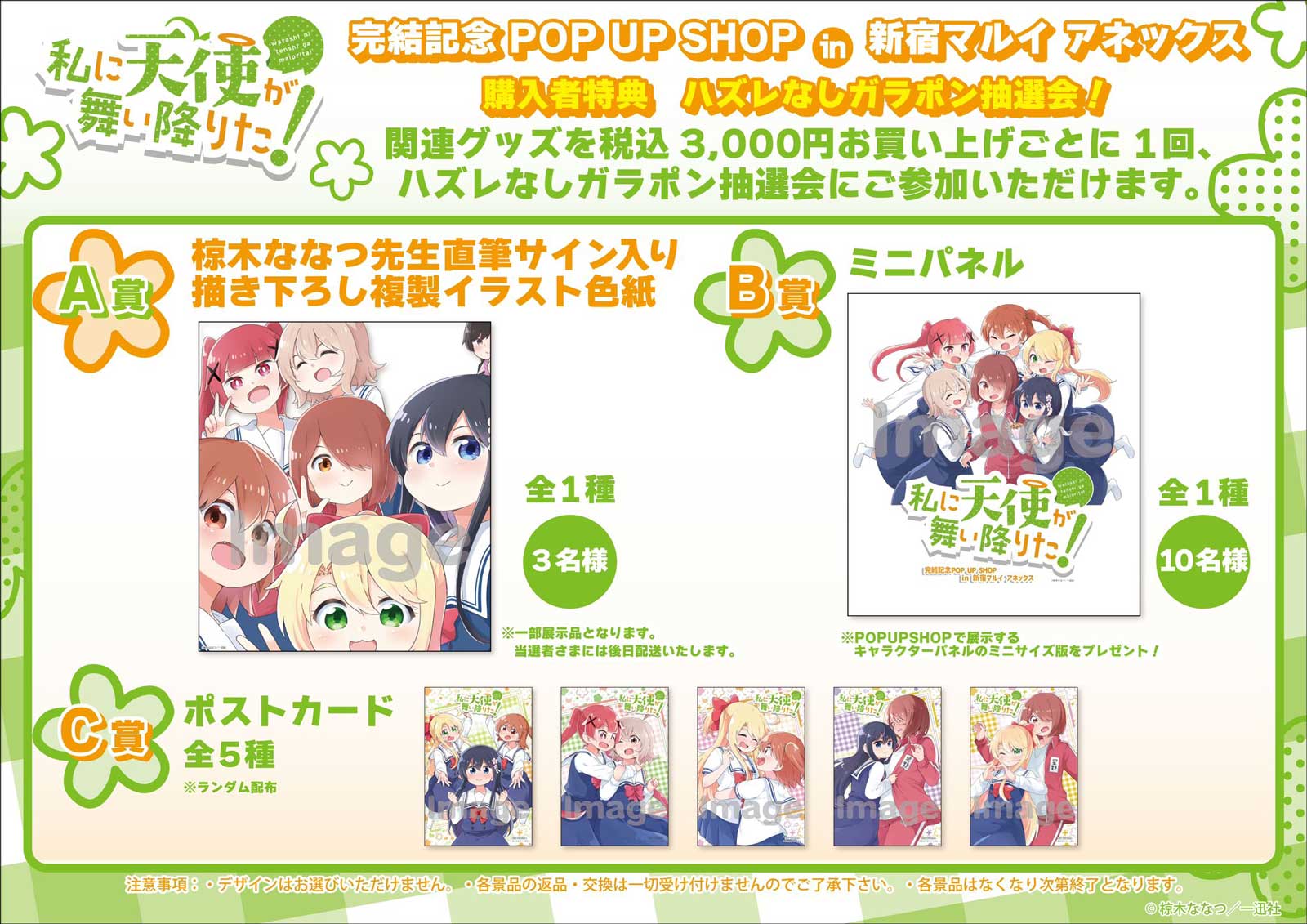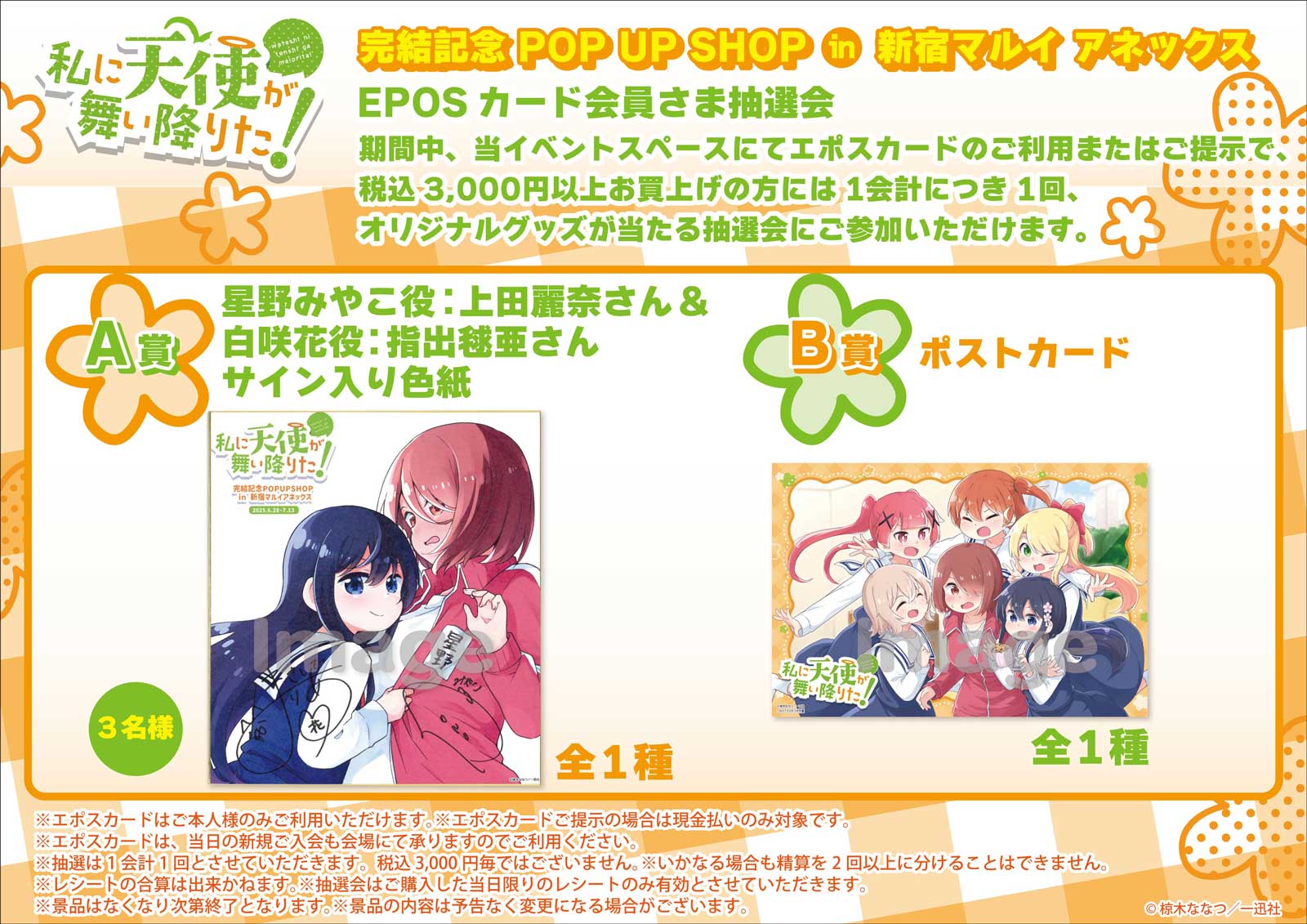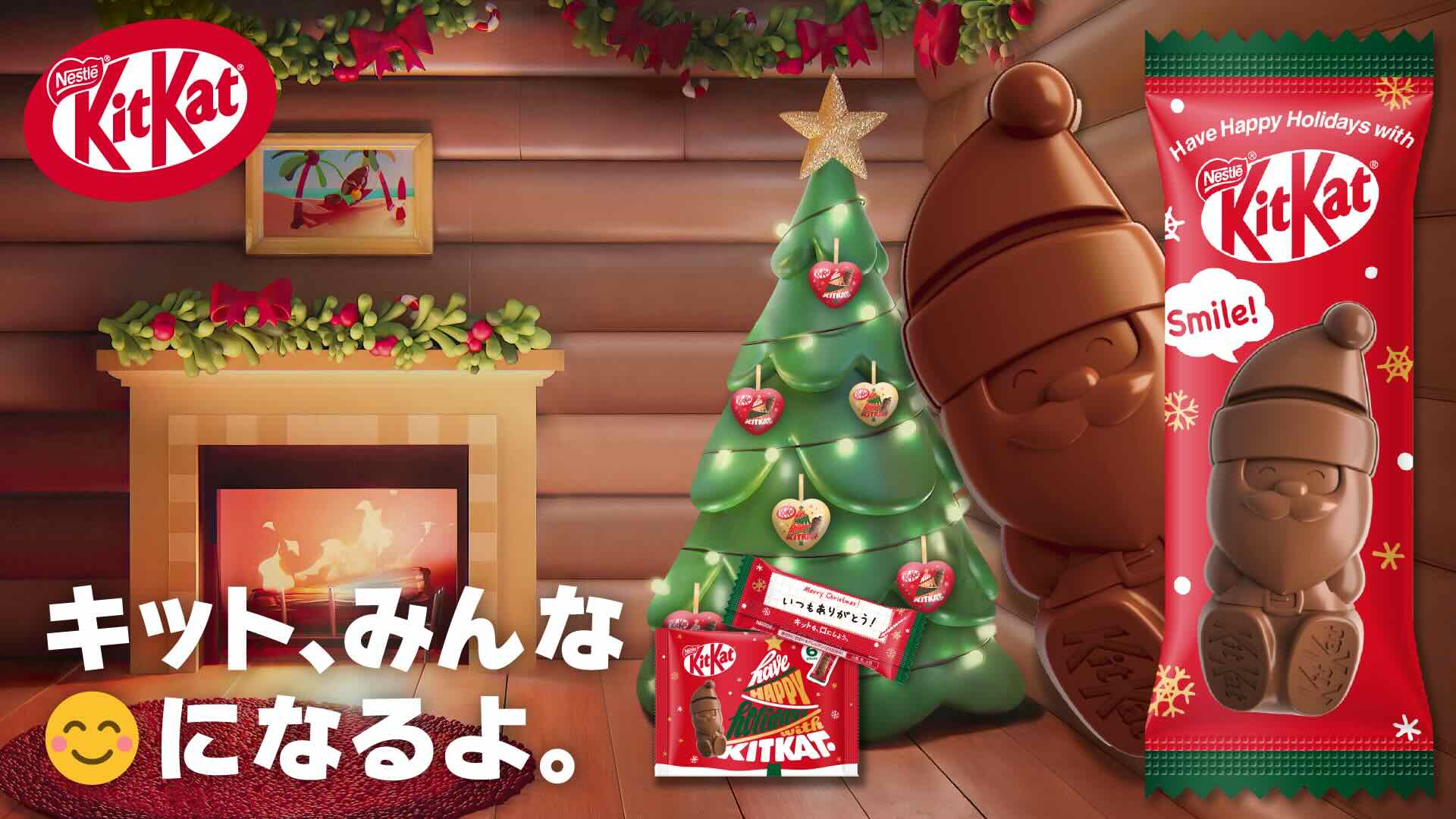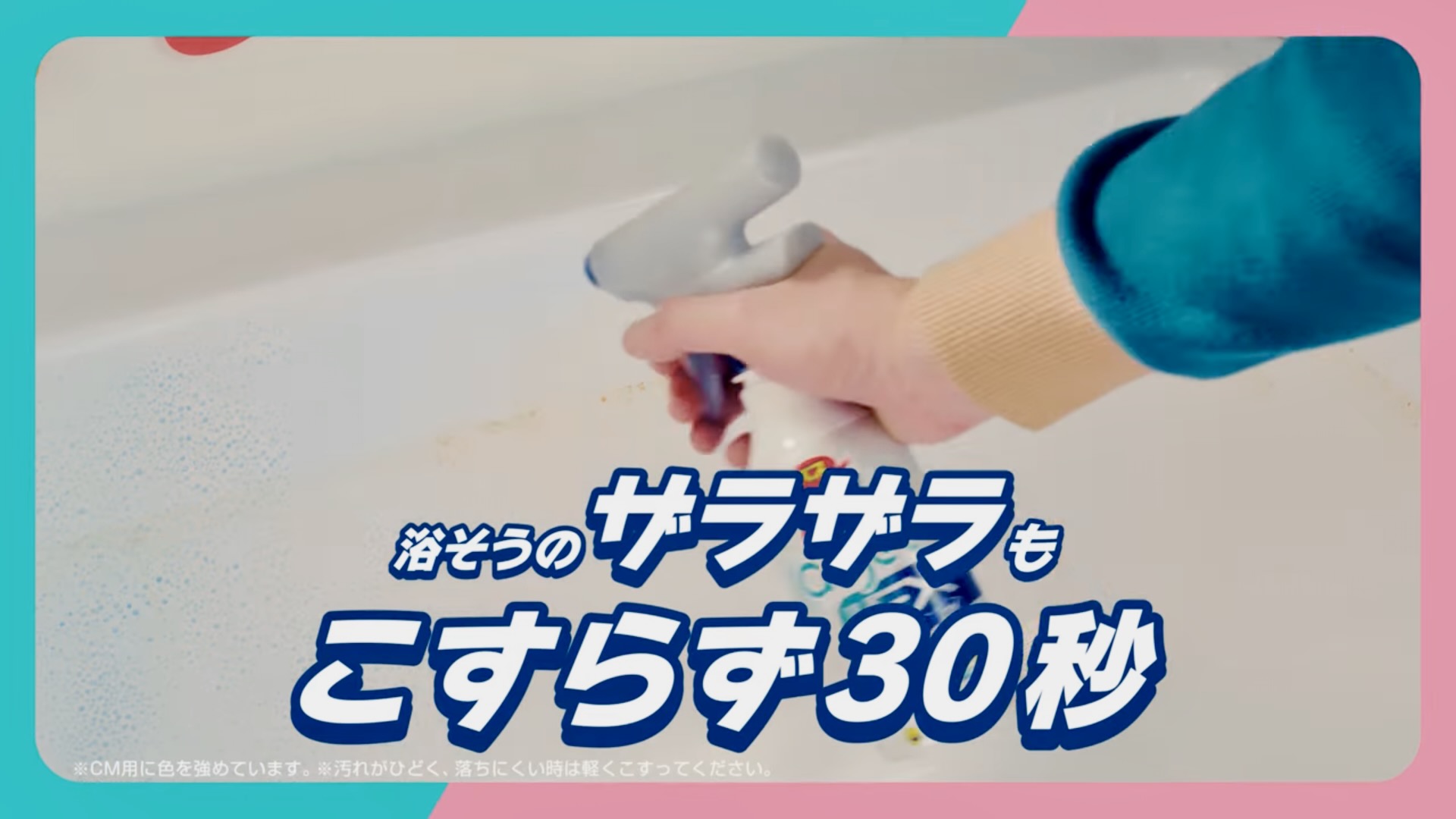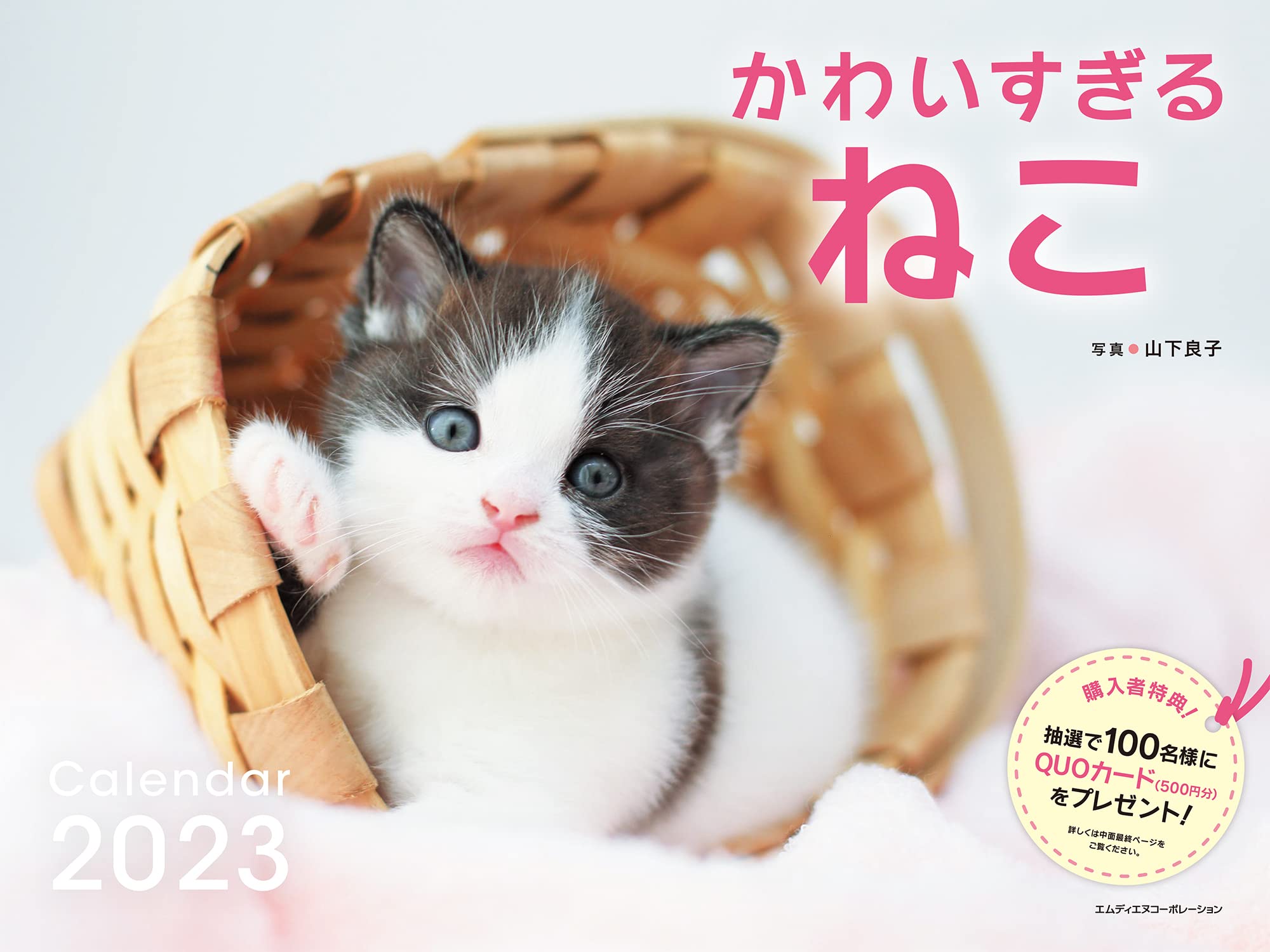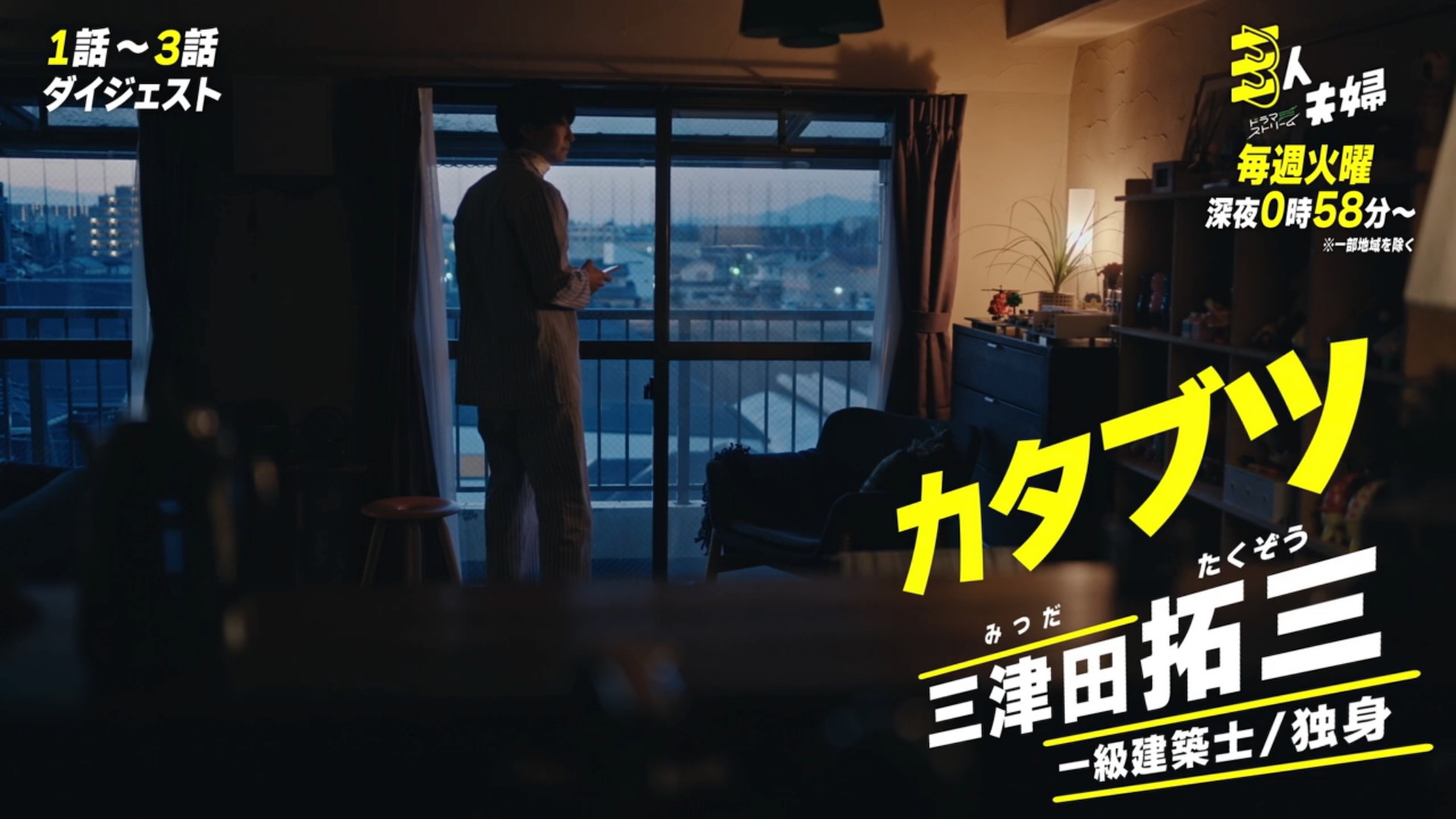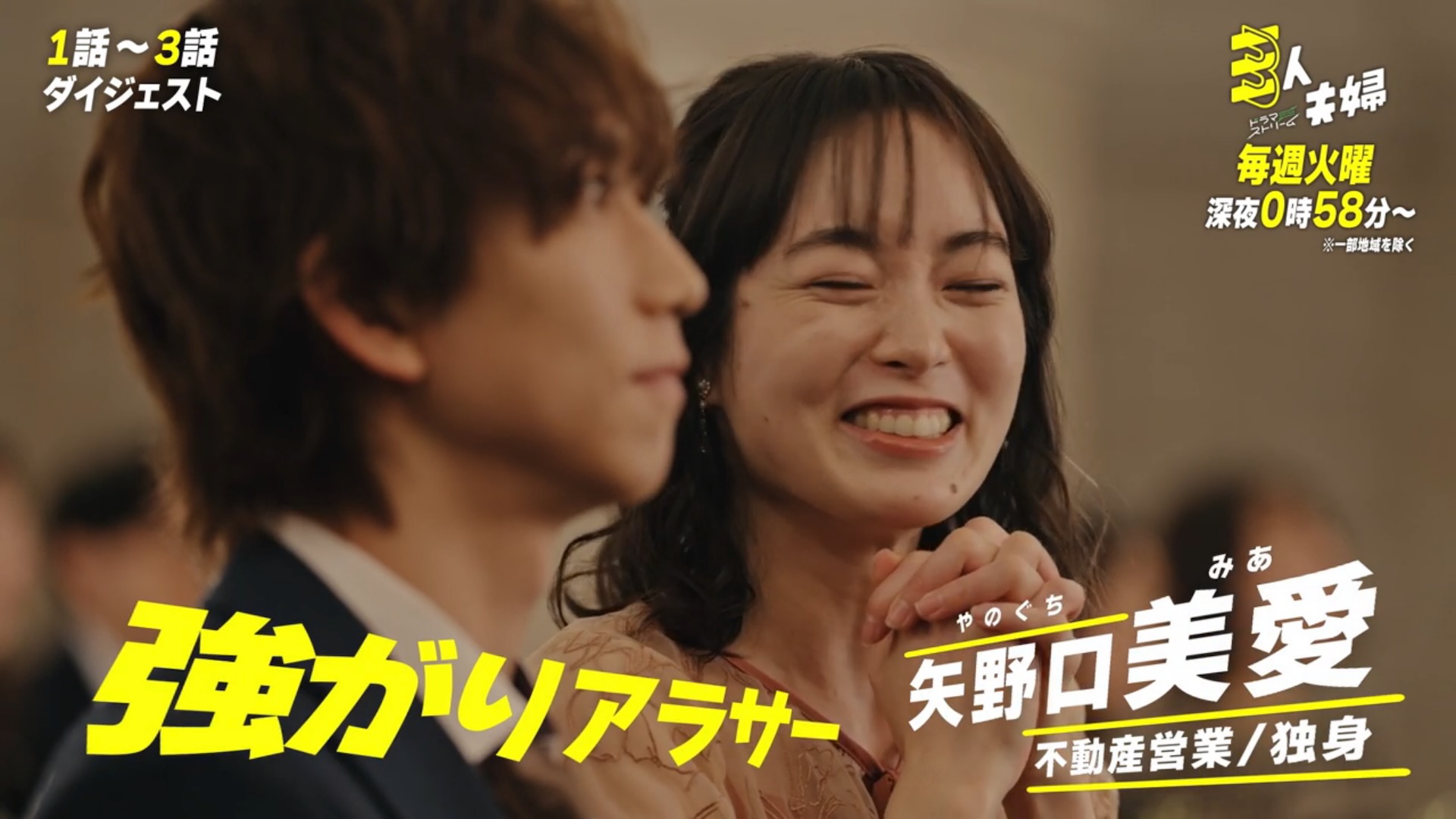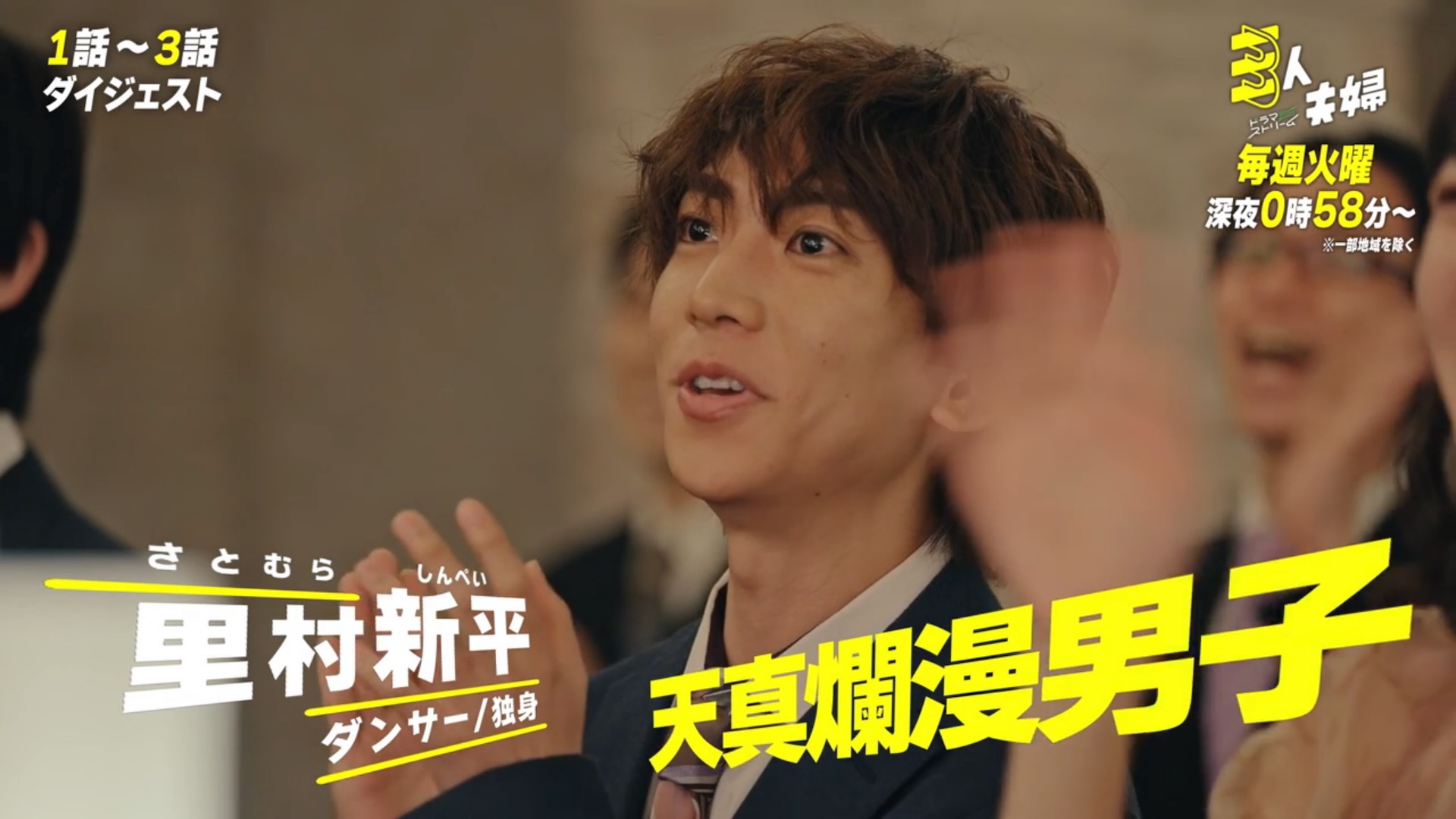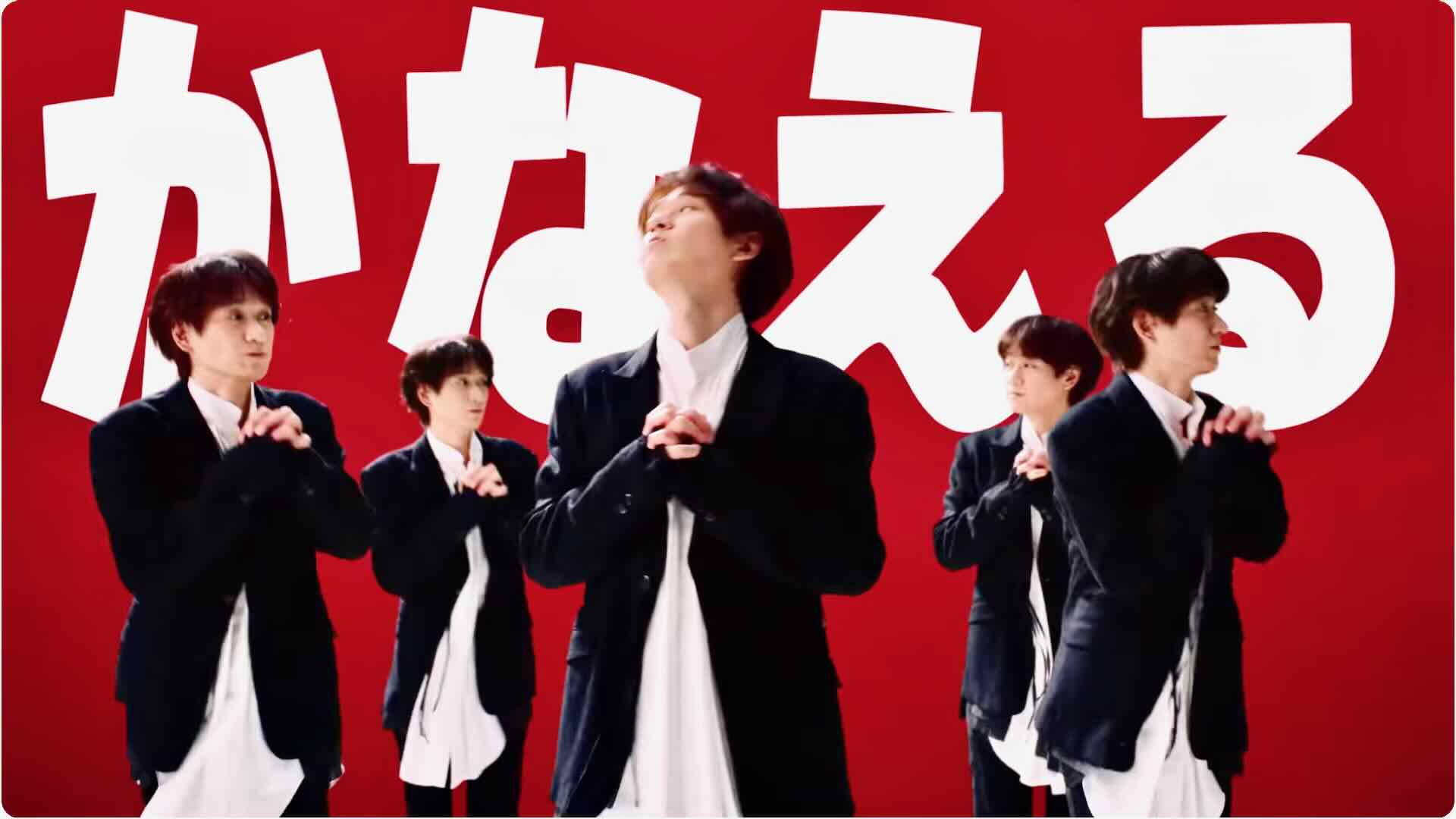
フォントワークスやモリサワから販売され親しまれている、かな書体「わんぱく」
広告画像 さとうゆたか
お好み揚げかまぼこ。
他に、ニタラゴや墨東も使われている。
これも。
防犯ポスター さとうゆたか
わんぱくルイカの使用例。
奈良県警橿原署のポスターかな。
車内吊りポスター さとうゆたか
京成電鉄に乗ったとき発見。
「矢切の渡し」には何度も乗っている。
知人を連れていったこともあったな…。
プールのポスター さとうゆたか
「プールWAI」は、ルイカ書体(英字のIの形で判る)で、
その上下の小さな文字が「わんぱくルイカ」書体。
テレビ番組 さとうゆたか
NHK 木村多江の、いまさらですが・・・
メキシコ・ルネサンス 〜芸術による国家再生とある日本人画家の活躍〜
背景に「あられ」書体が使われている。
これも。
もうひとつ。
テレビ番組 さとうゆたか
NHK Eテレ ギョギョッとサカナ★スター。
ファミマのキャンペーン さとうゆたか
『あつまれ どうぶつの森』キャンペーン。
広告画像 さとうゆたか
わんぱくルイカの使用例。
この商品、SNSでバズっているらしい…。
こちらでは、ルイカも使われている。
もう1点。
広告画像 さとうゆたか
わんぱくルイカ。
ジャパネットたかたの広告。
これも。
もうひとつ。
この「設」の文字で「わんぱくルイカ」と判明した。
テレビCM さとうゆたか
わんぱくルイカ。
アデランス、新・定額増毛 ファーストパック。
これも。